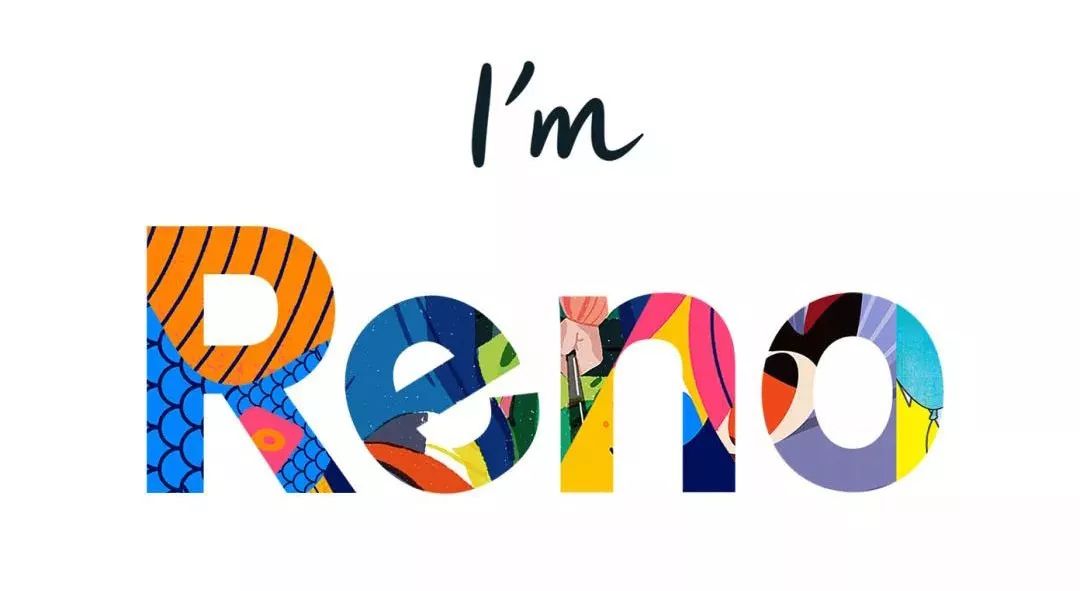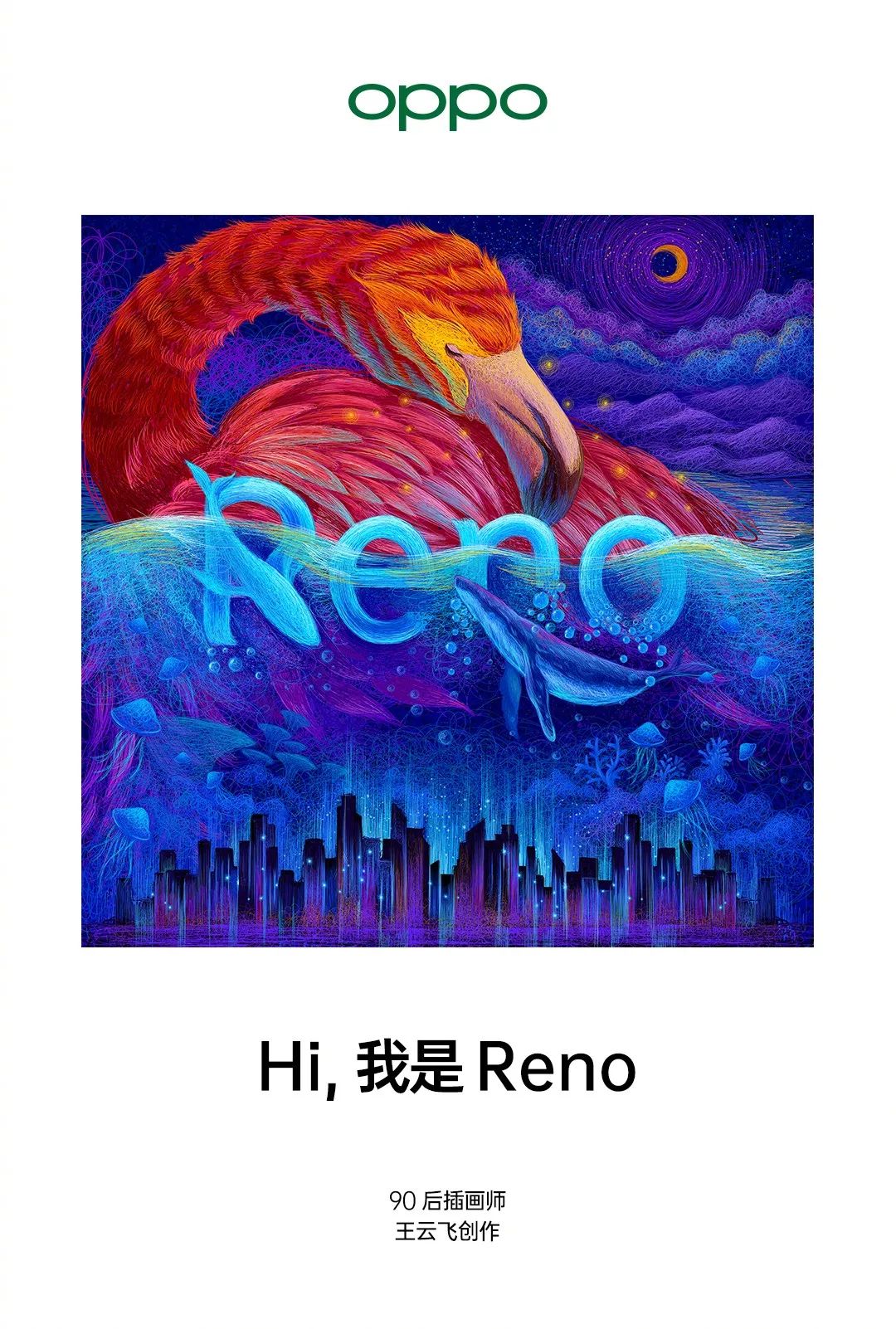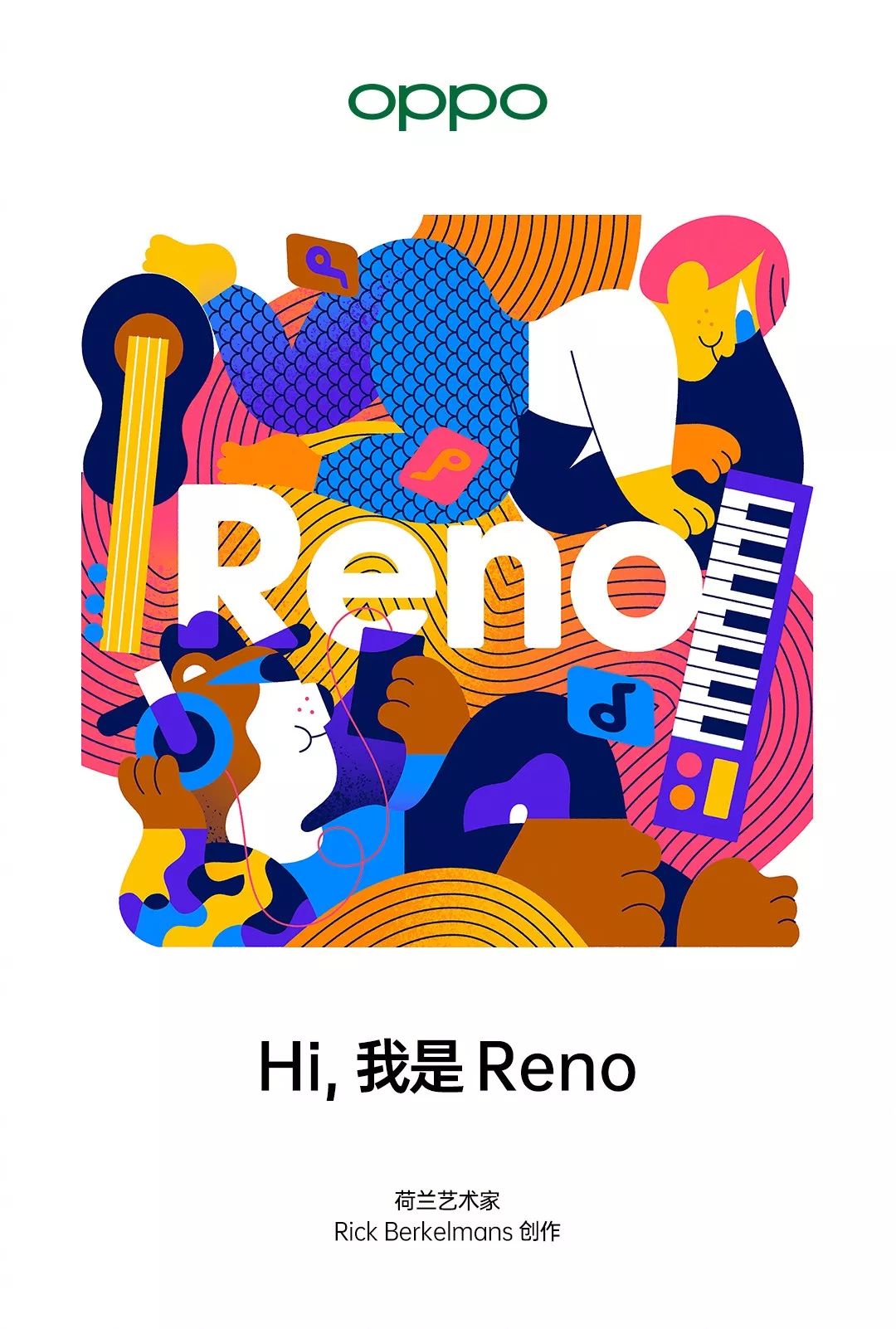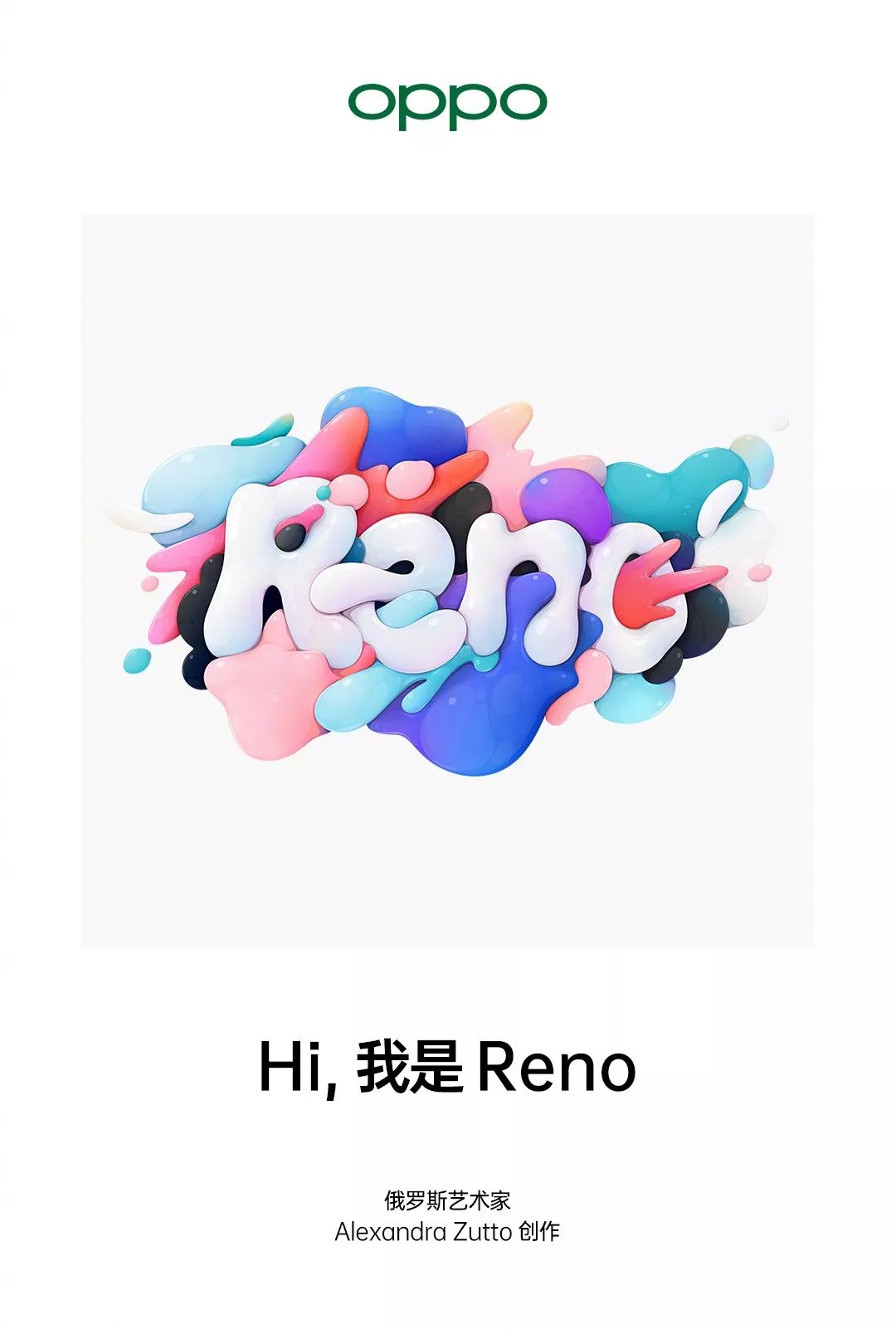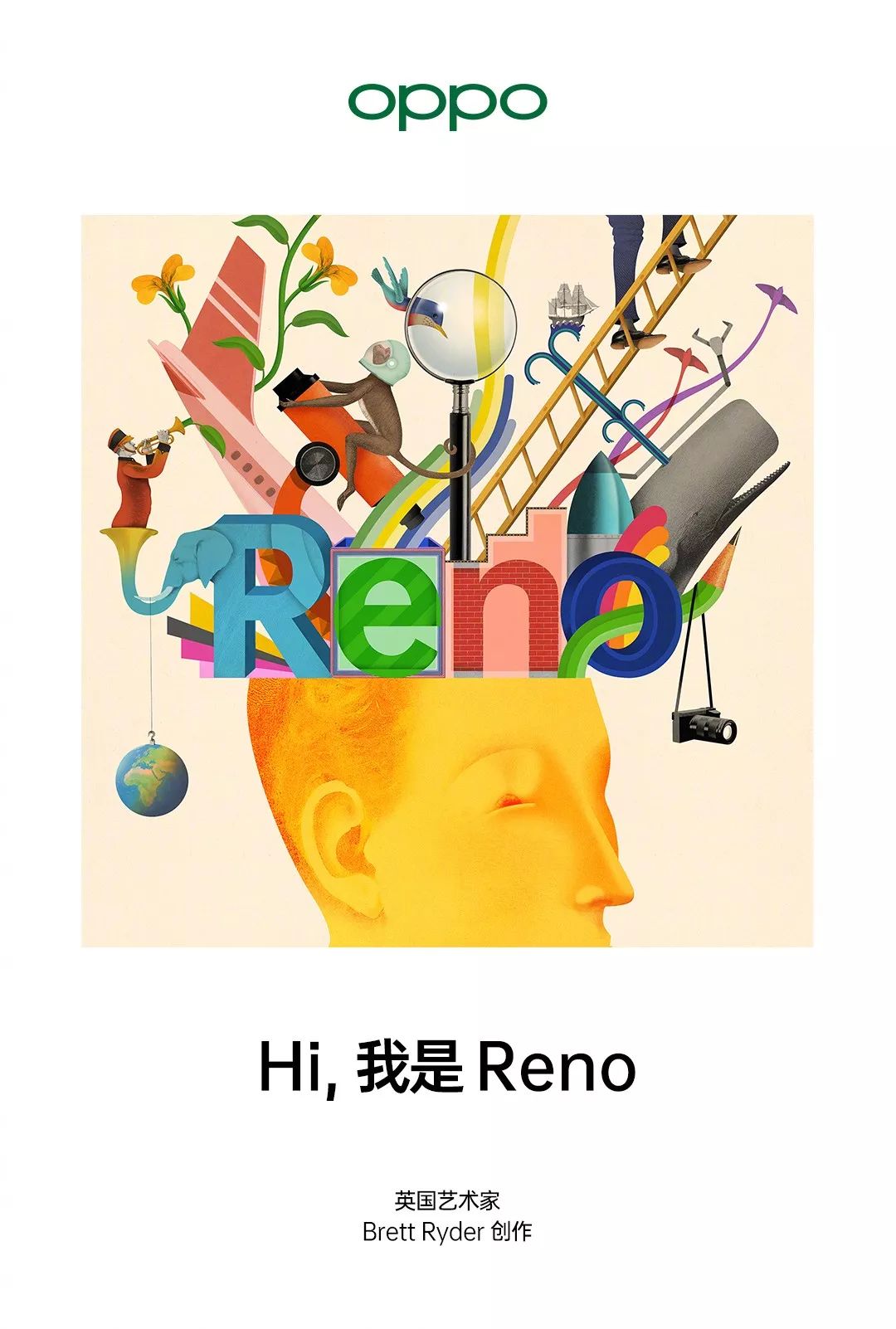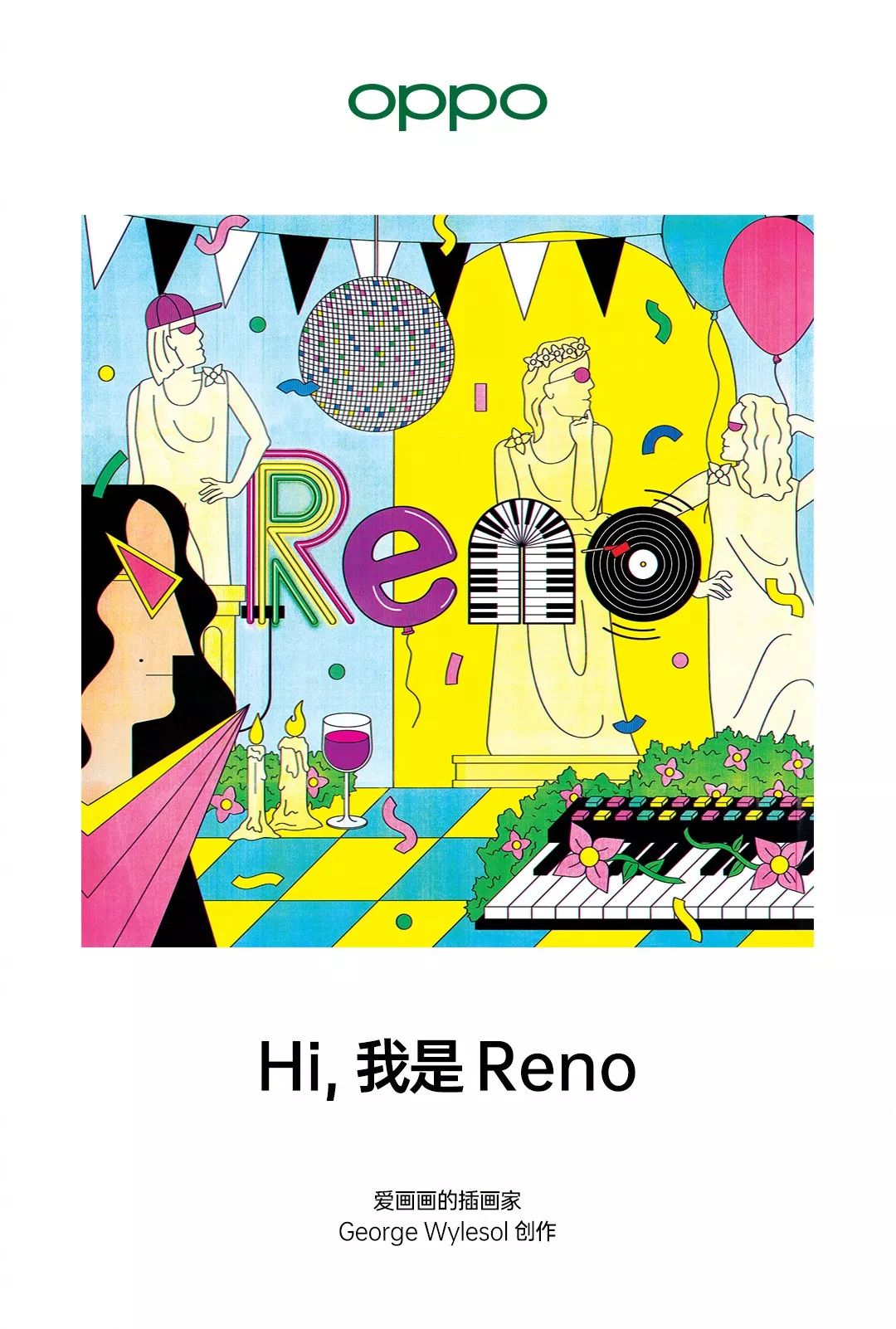
OPPO新推出的Reno,有点好看哦~
最近的手机圈
可以说是非常热闹
你看,前段日子
vivo推出了全新子品牌iQOO
OPPO坐不住了
紧忙也来了一款全新系列
——Reno
并且推出了新Logo
新Logo和旧Logo对比:
颜色变得更绿了
字母P的缺口也都补上了
看上去更成熟稳重
但我个人感觉
还是偏爱旧Logo多一点
原来的比较有活力
辨识度高些
你们感觉如何呢?
好了看完Logo
咱们回到OPPO新系列上
自Reno公布之后
不少网友都认为Reno
是OPPO的子品牌
其实并不然
Reno只是新系列!
那么,问题来了
Reno这个怎么读???
关于Reno的读法
网友们也是大开脑洞
里诺、雷诺、人哦
甚至还有人读成“热闹”
对此
官方给出了一份标准答案
应该这样读:ri:no
此外
对于这个名字的由来
网友也忍不住YY了
为了宣传新产品Reno
OPPO还为其打造了一组
来自全球各地的艺术家
创作的插画
用绘画来诠释Reno
我做了一个有关 Reno 的梦。
梦里城市长居深海,
火烈鸟与鲸鱼在夜晚相遇,
迸发出浪漫的小火花。
从璀璨的宇宙星云,
到日常的海滩屋顶。
Reno就像望远镜,
带我看到更大的世界。
在想象力的世界里,
Reno的颜色没有唯一。
在音乐世界里狂欢,
还有Reno时刻相伴。
想象中的Reno强大得像超人,
创造闪电般速度。
你的脑袋里装着奇思妙想,
Reno也是。
当古典主义的雕塑
带上嘻哈的鸭舌帽,
Reno有着联结
复古与未来的神奇魔法。
据说,每一幅画作里
都藏着Reno新系列的一项功能
可以说别具巧思
十分用心了!
看完OPPO新Logo
和这个新系列
大家觉得咋样呢?